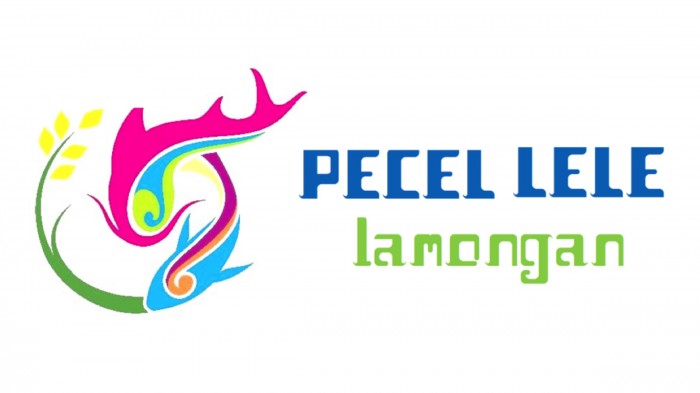
NICE WORK!!!!!!!!!!!!!!!!!!!!!!!!!!!!!!!!!!!!!!!!!!!!!!!!!!!!!!!!!!!!!!!!!!!!!!!!!!!!!!!!!!!!!!!!!!!!!
NICE WORK!!!!!!!!!!!!!!!!!!!!!!!!!!!!!!!!!!!!!!!!!!!!!!!!!!!!!!!!!!!!!!!!!!!!!!!!!!!!!!!!!!!!!!!!!!!!(2)
keren ja!!
budaya lokalnya kerasa banget! good job!
gila, kok keren kayak HONOCOROKO, bagus-bagus moga-moga kembarang mua buat typeface e sama bagus e kyk kamu meskipun uda pasti jelek sih dia
gila, kok keren kayak HONOCOROKO, bagus-bagus moga-moga kembaran mua buat typeface e sama bagus e kyk kamu meskipun uda pasti jelek sih dia
Nice fontstruction there, the javanese word content it's shown so nice
Very neat and well-crafted ^^ Probably if you equalize the stroke of small letters 'i' and 'j', it would look nicer~
Apikkk Jaa.. cmn rasane stroke huruf Z besar krg sama kayak lainnya
Bagus, budaya lokalnya terasa banget
buagussss jahhhhh. !!!!
bagus poooooool!!!
Looking really good so far. One minor problem, the lowercase is thinner than the uppercase, so it seems kind of weird to look at.
Nice :3 Glyph-nya juga lengkap lagi.
niiiiiiiiiiceeeeeeeeeeeeee fonttttttttt!!!
a sample for the font:)
Woow, very good. Beautiful fonts. I like it :)
Suka lengkung" nya
nice font! goodjob
Kuerennn!!!
really cool, 2 thumbs up for your typeface
Keren, rapi banget n detail
Wihhhhh kerennn jaaa!!!! Greattt jobb nemenn :))))
So cool!!
keren pol , cuman untuk U sama V nya agak mirip tapi untuk font yang lain sudah bagus
Cool font :3 Nice work
Keren! Bagus sekali!
weh keren
soooooo cute~ I can totally see your effort making that many there
Type face nya unik , budayanya kerasa sekali. Keep it up
Wah, Seni dan budaya nya kental sekali di Font ini.. Konsepnya luar biasa, dikerjakan maksimal hingga selesai,
mantap deh kerja kerasnya, tapi terbayar juga dengan hasilnya yang luar biasaaa!
VeRy well done!
sudah konsisten dan bagus!!
kok sangar. wkwkwk Great job! Two thumbs up!
nice font!!
nice font dja! Huruf M nya agak aneh tp overall semua bagus kok :D
Likee,,